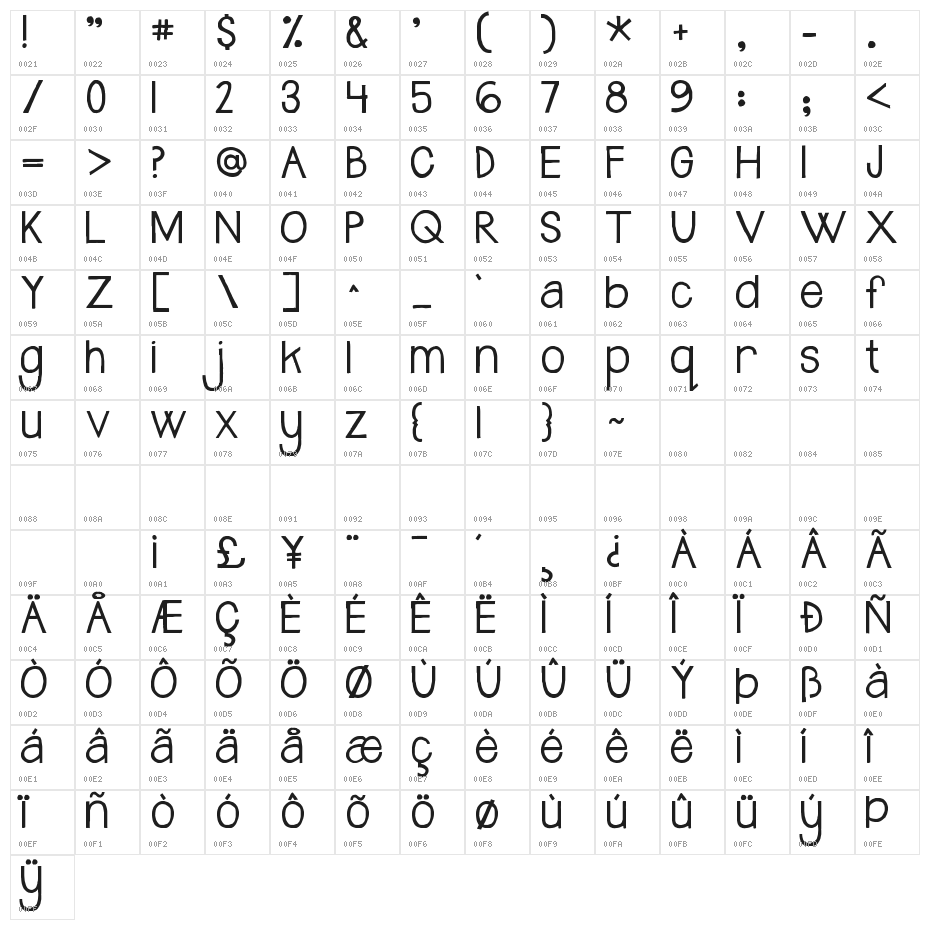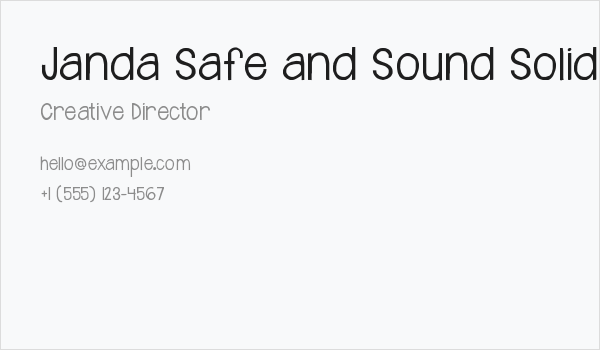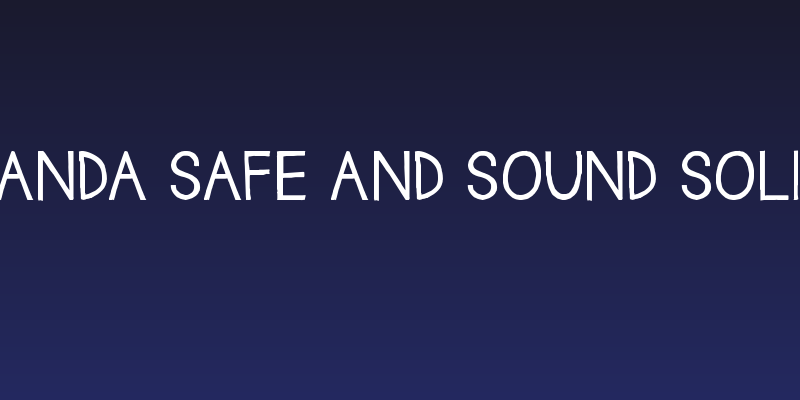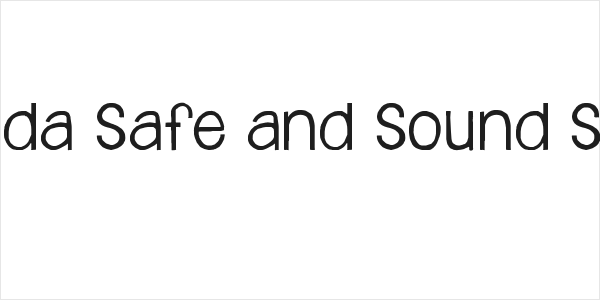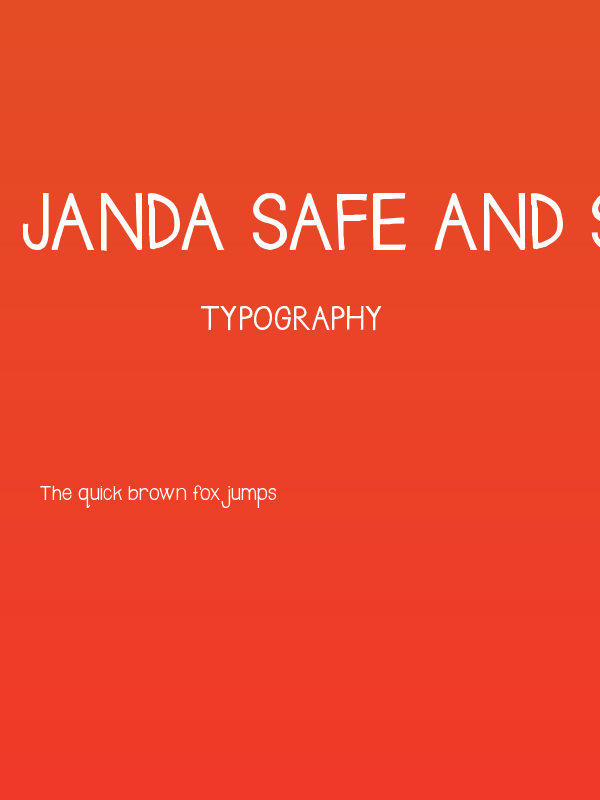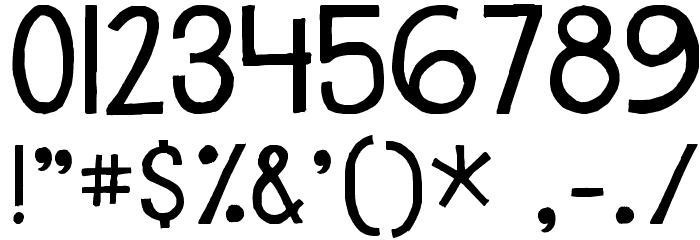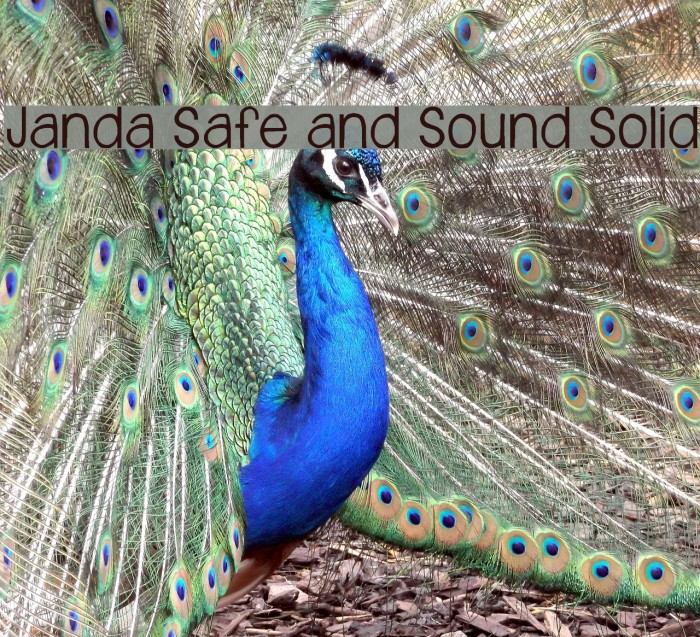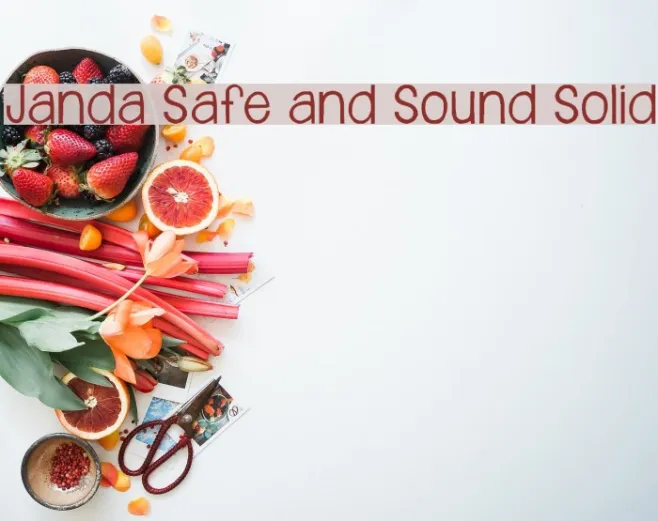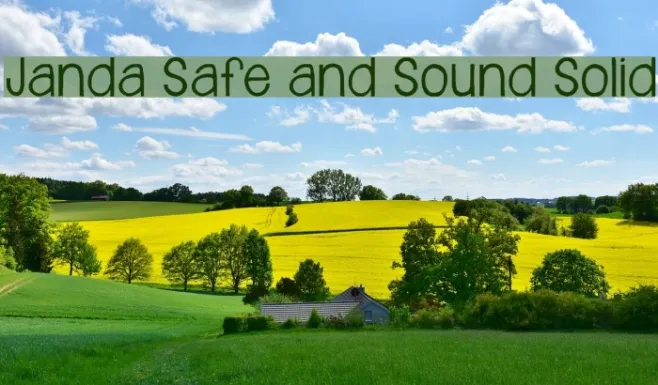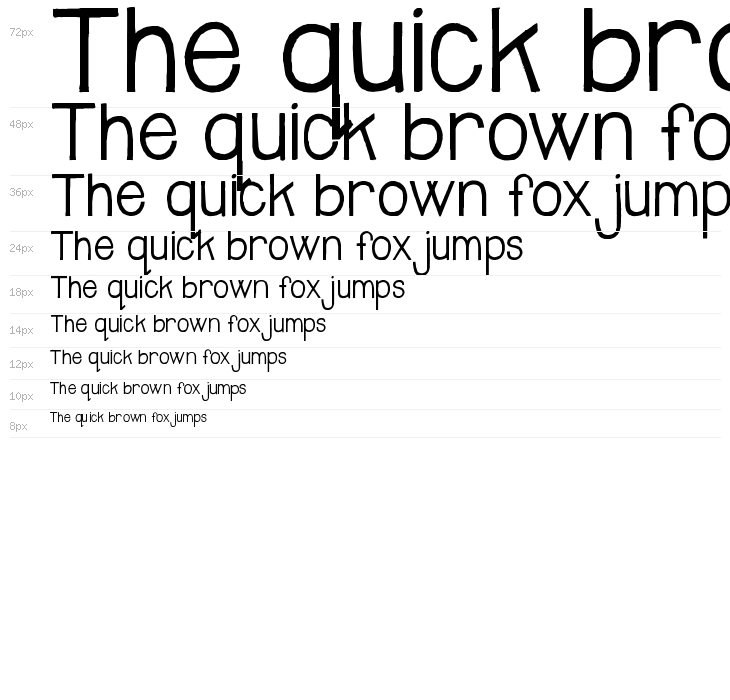
Janda Safe and Sound Solid Font
| Style général | Casual |
| Cas d'utilisation | Headlines, Informal text, Branding |
| Projets proposés | Ideal for children's books, greeting cards, informal invitations, and playful branding. |